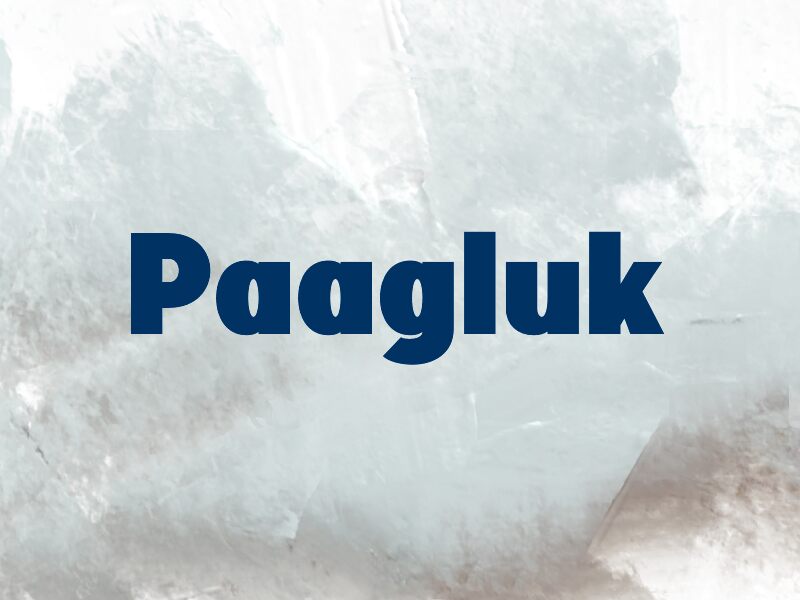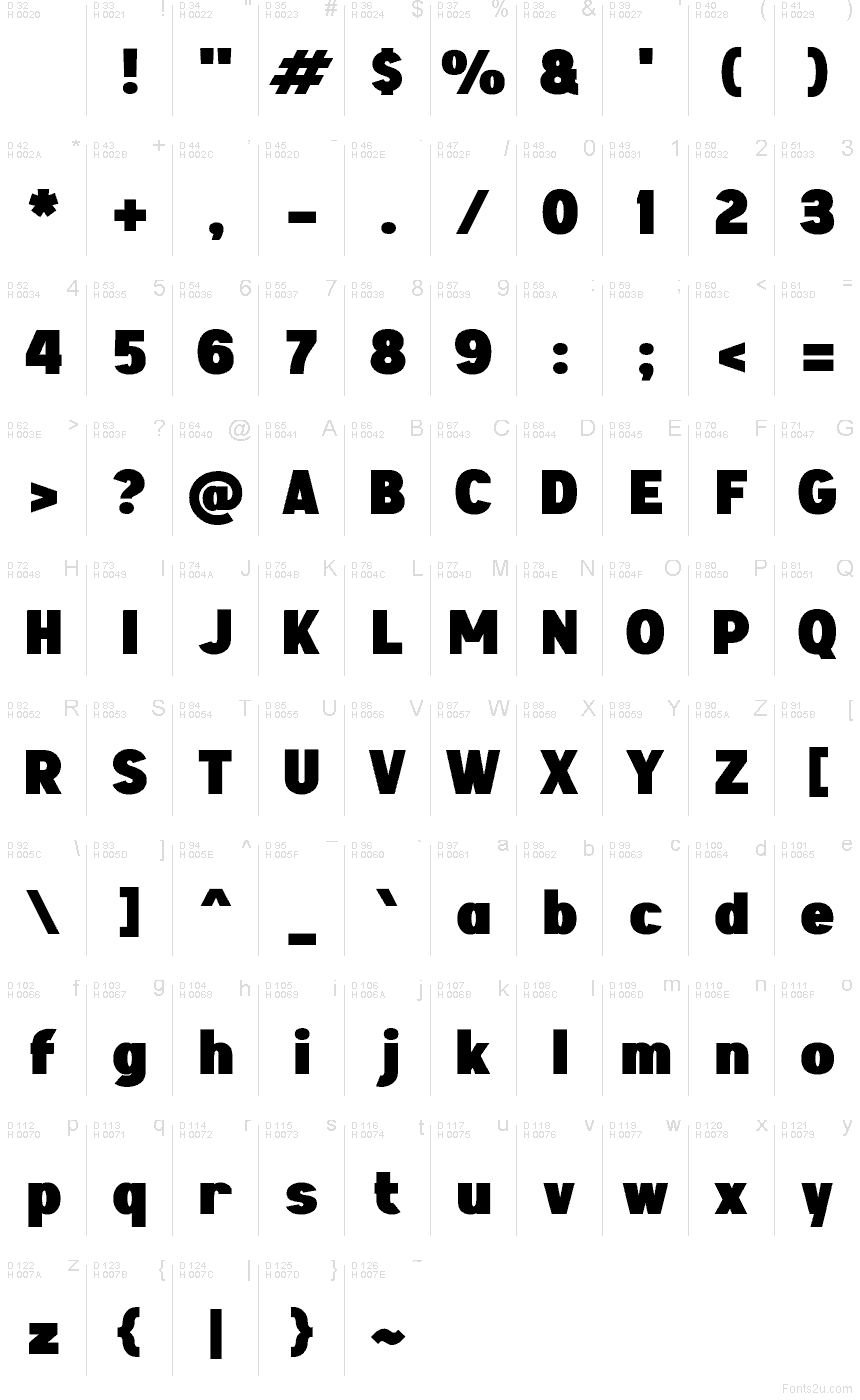
Paagluk
Paagluk von wep ist eine massive, serifenlose Schrift mit einem stumpfen, fast spielerischen Charakter. Die Buchstaben sind kompakt und wuchtig; abgerundete Ecken und enge Innenformen sorgen für eine freundliche Dynamik, die das Gewicht der Schrift gekonnt auflockert.
Die Schrift eignet sich ideal für Snack-Verpackungen, Streetwear-Brandings, Plakatüberschriften, App-Splashscreens, Musik-Artworks oder kurze Texte, bei denen ein massiver Font allein schon die Seite trägt. Nutzen Sie ihn für Titel, markante Cover-Zeilen oder einfache Wortmarken, wenn Sie statt einer sterilen, neutralen Sans ein Design mit weicher Geometrie und kräftiger Silhouette suchen.